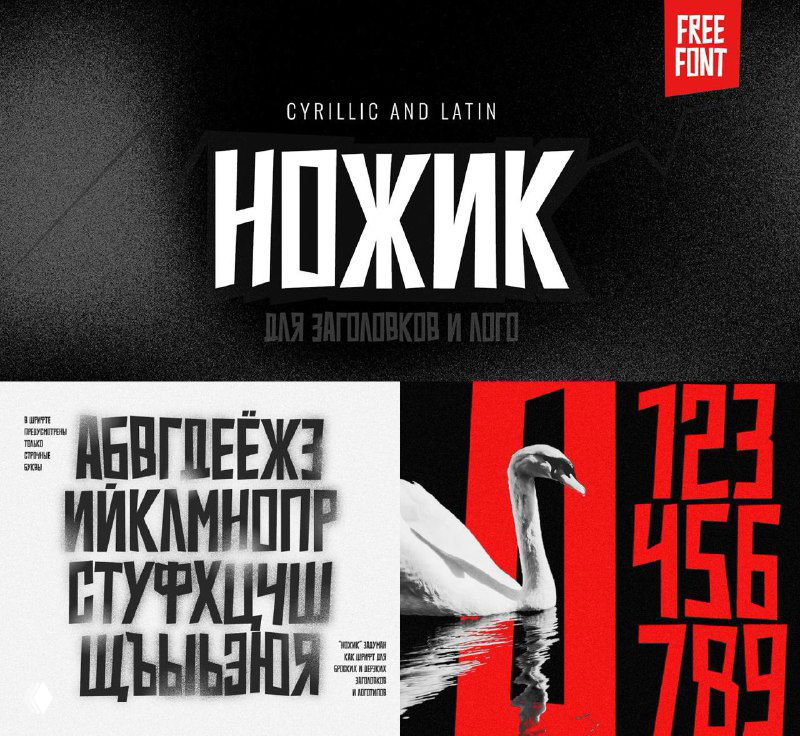
Выразительный декоративный шрифт с острыми резкими формами. Хорошо подойдёт для использования в плакатах, логотипах, заголовках на сайтах и даже мемах.